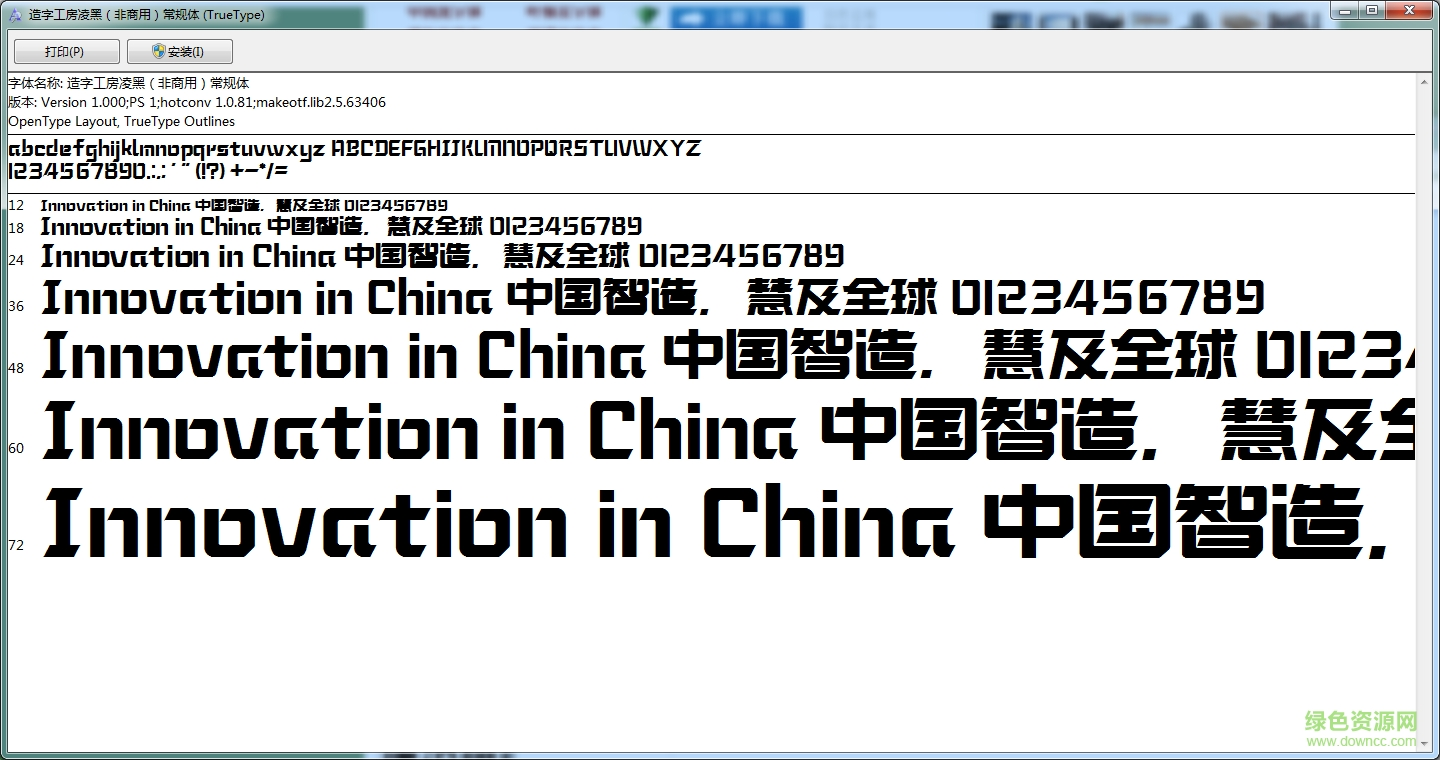
软件介绍 软件标签: 造字工房凌黑体 造字工房 造字工房凌黑体是一款端正简洁的中文简体字体,此款字体线条较粗,字型端正,整体效果非常出色,广泛的应用于名片设计、包装印刷、平面设计等各行各业,喜欢的朋友欢迎来绿色资源网下载!字体安装方法方法一:控制面板/字体/文件/安装新字体;方法二:直接将字体复制到C:\WINDOWS\Fonts。方法三:针对win7系统,用户只需选中字体右键安装即可。注意事项本站所有字体资源仅供个人学习与参考,如需商业使用请到相关官网授权。 软件截图 上一张下一张(1 / 1) 安装详细截图 其他版本下载 标题 大小 更新日期 下载 下载地址 电脑版 造字工房凌黑体 点击报错 软件无法下载或下载后无法使用,请点击报错,谢谢! 关闭报错反馈 请描述您所遇到的错误,我们将尽快予以修正,谢谢! *必填项,请输入内容 本类最新 dreamweaver字体库 首尔南山体字体 v1.06 官方版 潮字社风云简ttf 潮字社凌渡鲲鹏简体字体 潮字社曾玉波手书简字体 微博慧心字体 用户评论 热门评论 最新评论 发表评论 查看所有评论(0) 昵称: 请不要评论无意义或脏话,我们所有评论会有人工审核. 字数: 0/500 (您的评论需要经过审核才能显示)